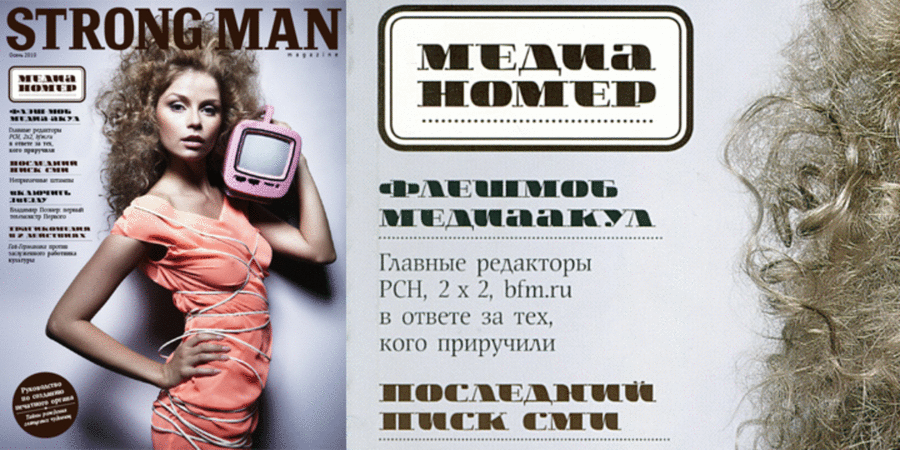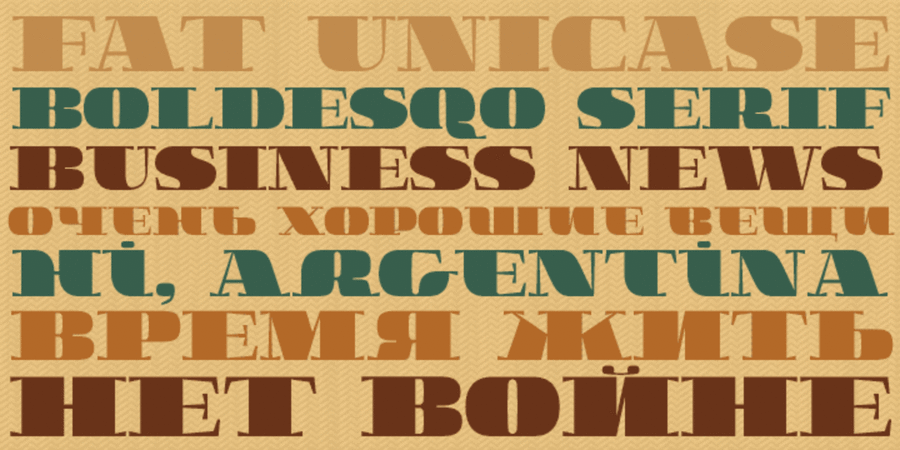
Жирный широковатый сериф для заголовков и плакатов. Разработан Сергеем Ткаченко в 2010 году.
Асоціації з сімейством шрифтів Boldesqo Serif 4FОсобистість і характер гарнітури:
переконливий, важкий, стійкий, сильний, самобутній, пузатий, товстий, старомодний, оригінальний, характерний, дорогий, екстравагантний, химерний, циганський, помітний, яскравий, величезний, демонстративний, артистичний, виразний, спекотливий, спекотний, твердий, південний, красивий, багатий, дерев'яний, ремісничий, сміливий, різкий, претензійний, естетський, нонконформістський, експериментальний, активний, крафтовий, пивний, тропічний, нахабний, запальний, старовинний, золотий, ажурний, святковий, ювелірний, осінній